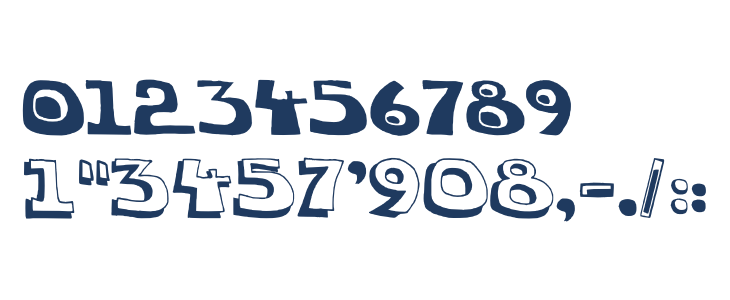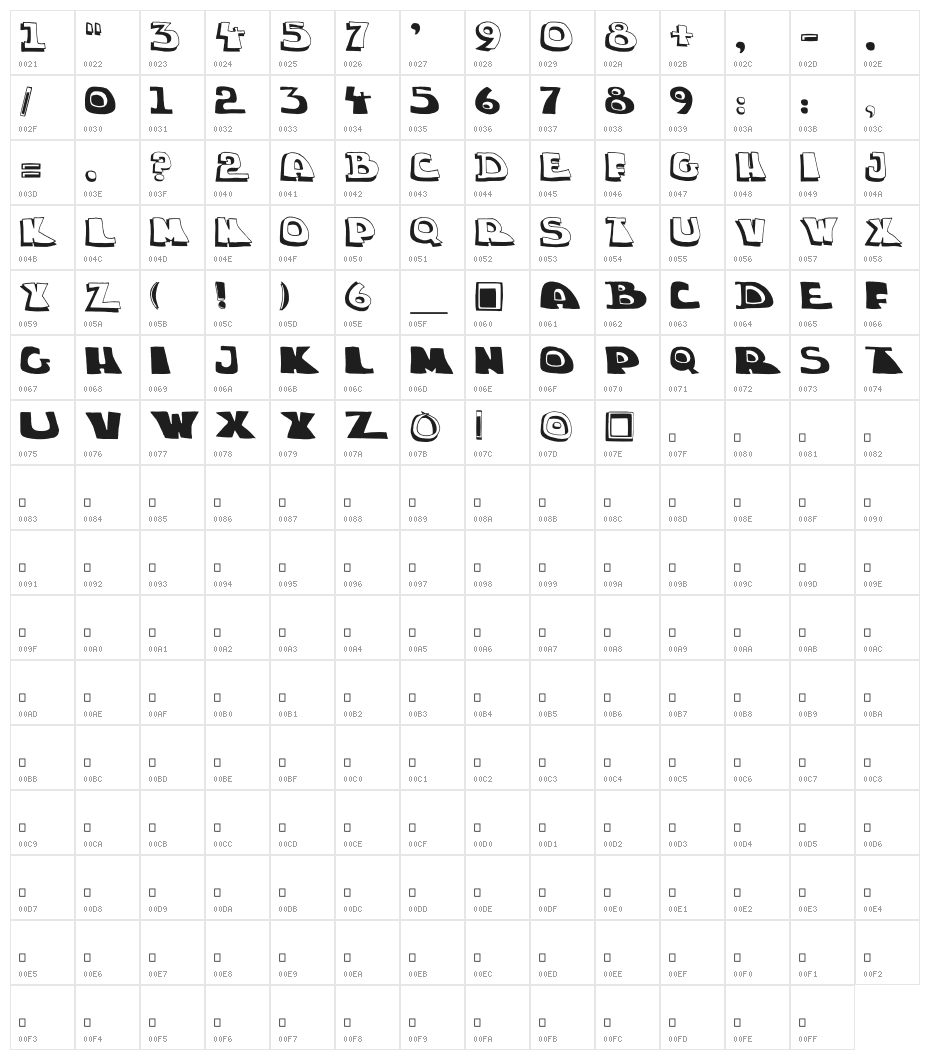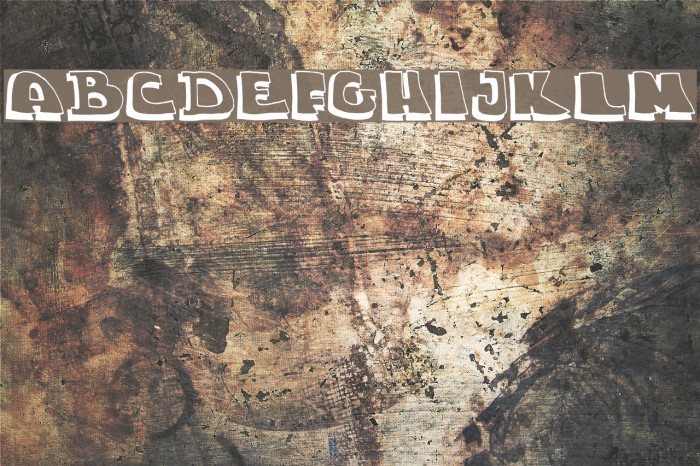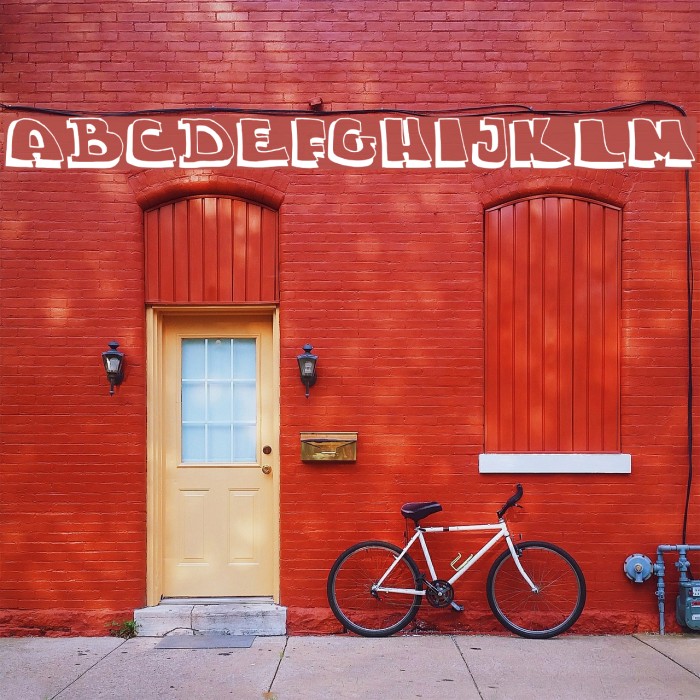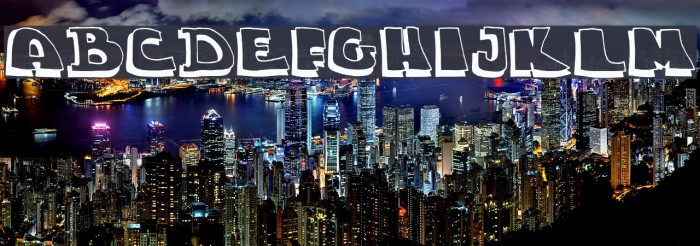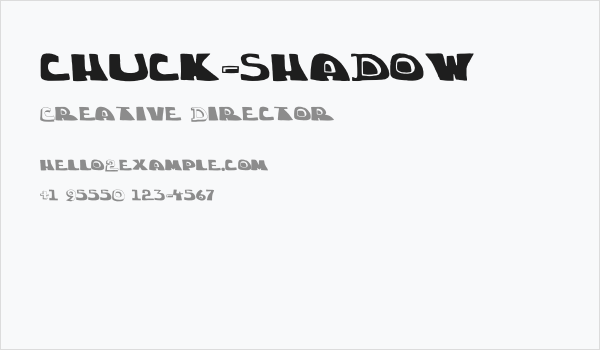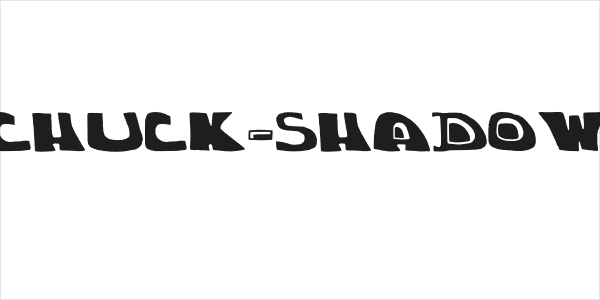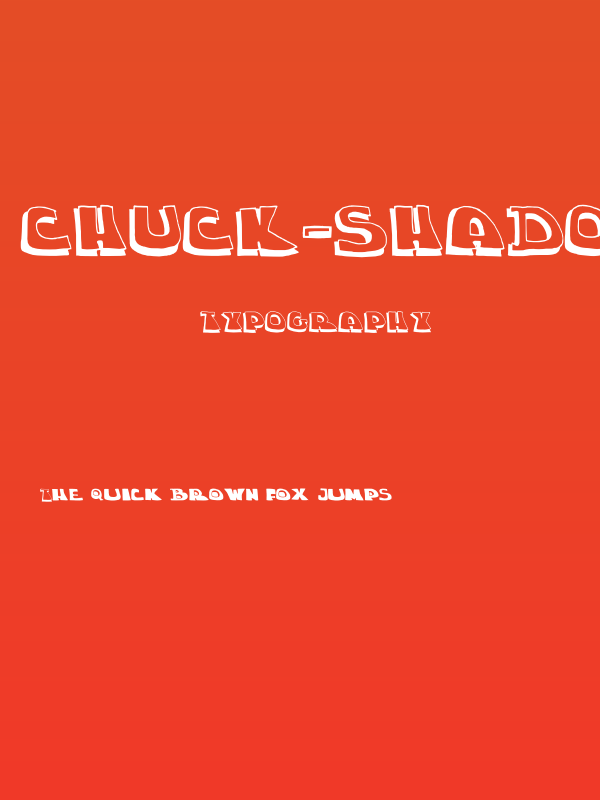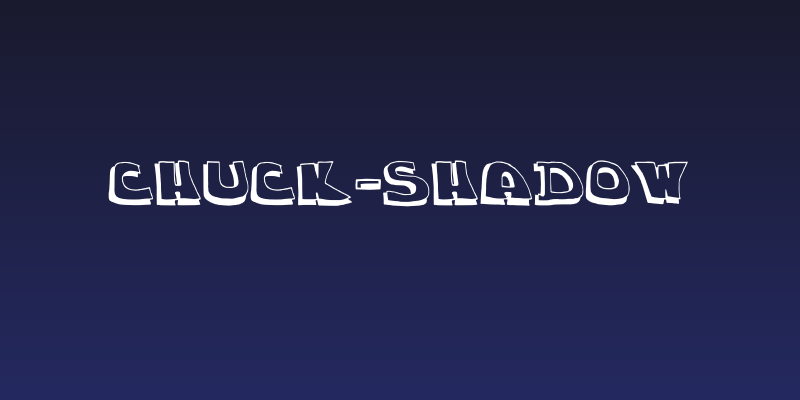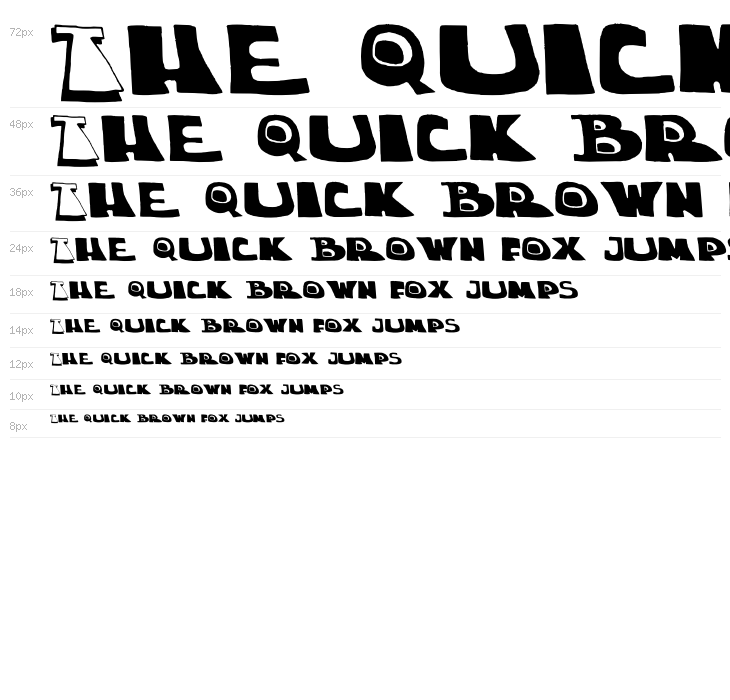
chuck-shadow Font
| Stile generale | Playful, Comic |
| Caso d'uso | Headlines, Posters, Branding |
| Progetti proposti | Perfect for comic books, children's book covers, playful branding, posters, and eye-catching headlines. |